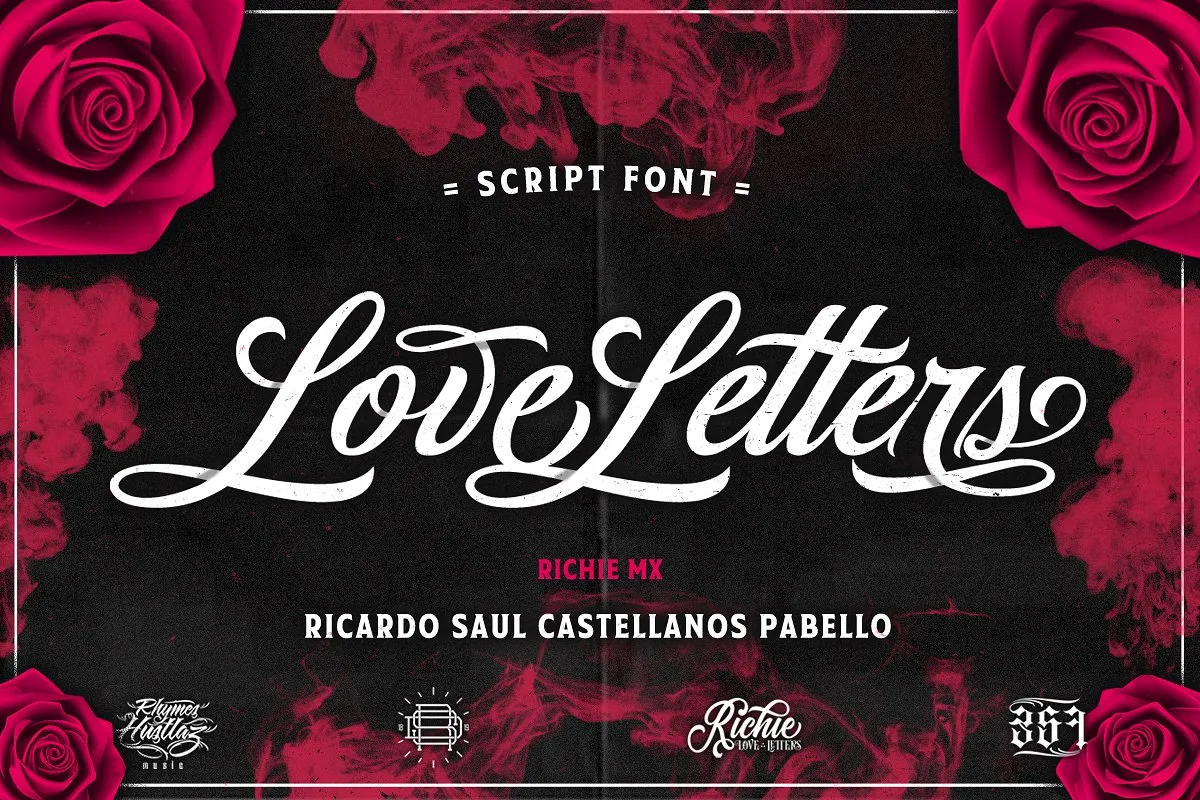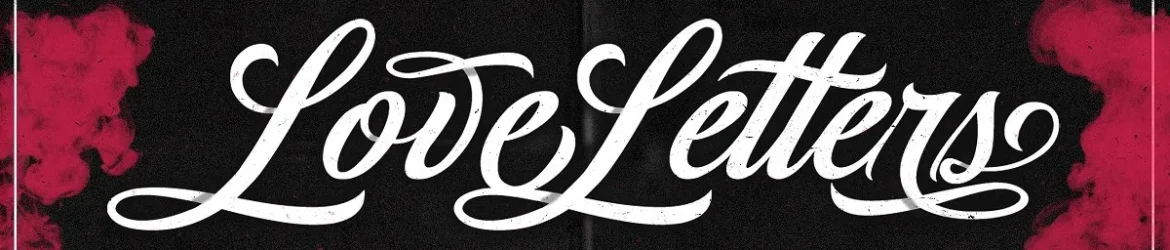
Love Letters Script Font – Download Grátis
Esta é uma fonte tipográfica escrita a mão com estilo chamigrafia clara e bom fluxo. É excelente para seu próximo projeto criativo. A fonte Love Letters, criada pelo Richie Mx, inspirou-se no estilo de letras Script Lettering. Esta fonte se adequa perfeitamente para uso como logotipo, designs de produtos, rótulos, água-marinha, posts nas redes sociais, vestuário, convites, placas, clubes esportivos ou motor/carro, eventos especiais, qualquer coisa que precise da aparente autenticidade da escrita a mão. A fonte Love Letters Script é uma criação e compartilhamento do Designer Riders on the Storm Design. Se você está procurando por uma fonte de estilo chamigrafia com um ar romântico e personalizado, esta pode ser exatamente o que você precisa para dar vida aos seus projetos.